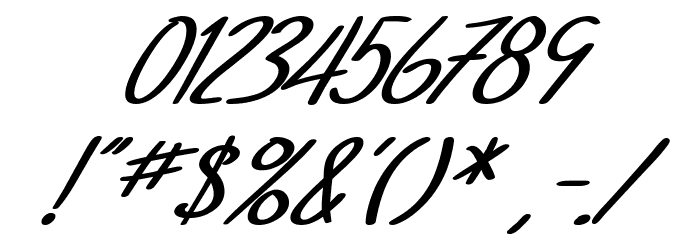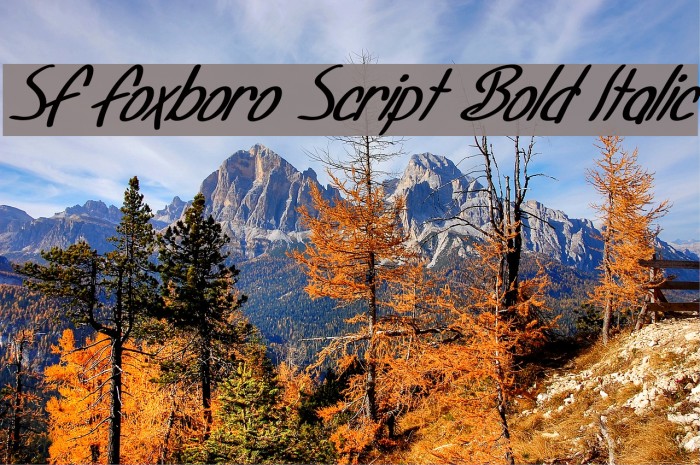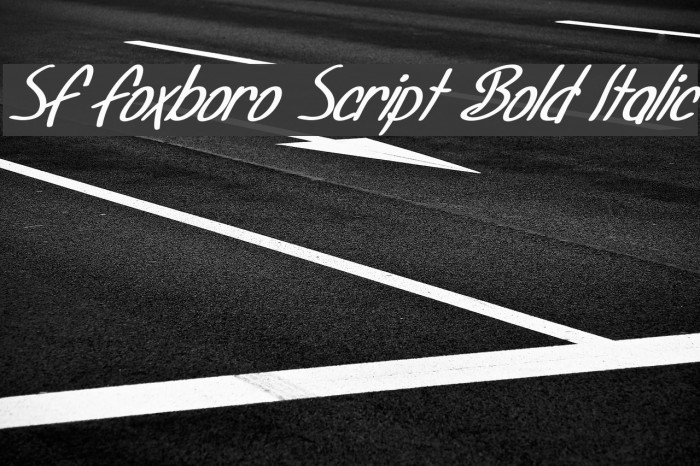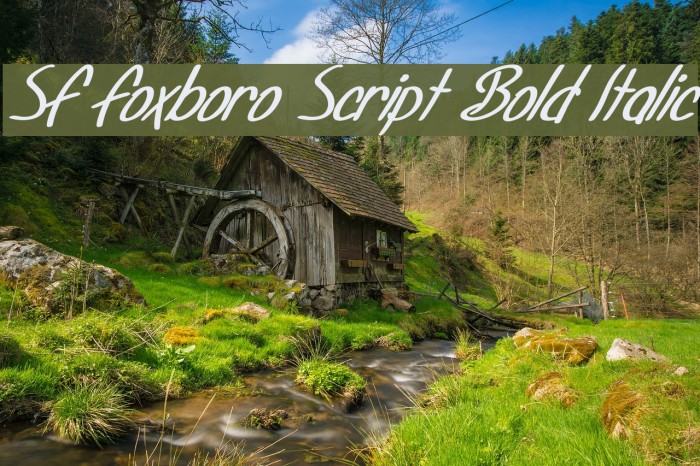
SF Foxboro Script Bold Italic Font
| Anwendungsfall | Logos, Invitations, Greeting Cards |
| Vorgeschlagene Projekte | Ideal for wedding invitations, greeting cards, branding projects, and any design that requires an elegant, personal touch. |